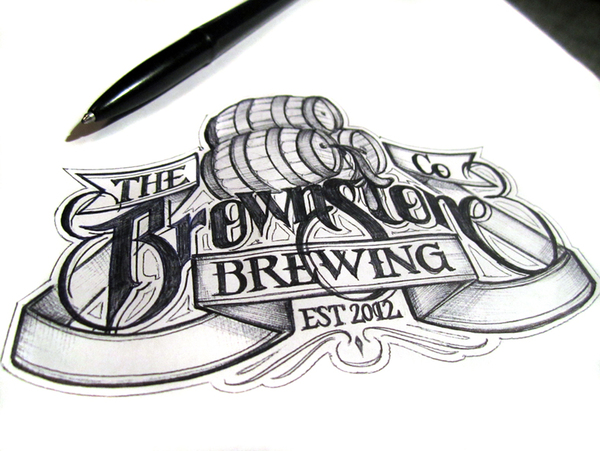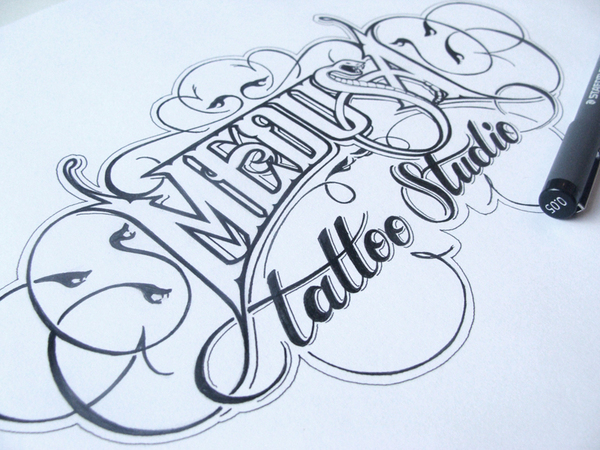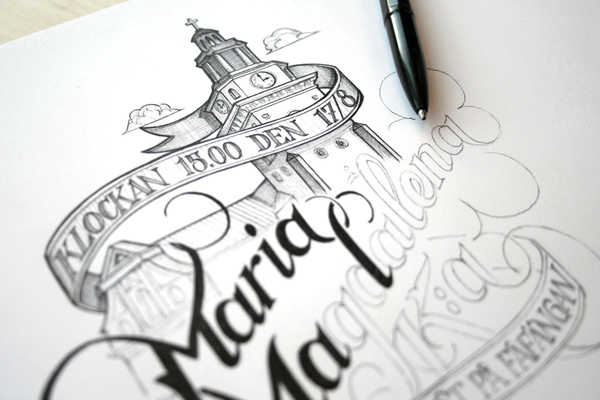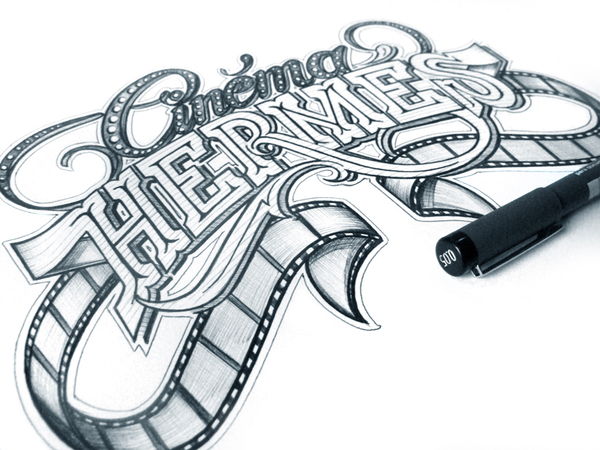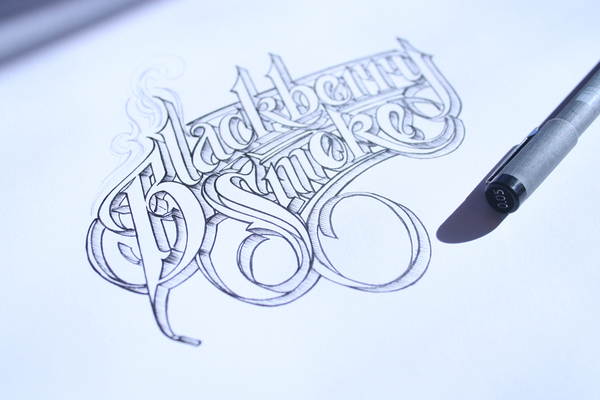
Martin Schmetzer
Por Lettering Time hemos visto pasar grandes diseñadores y artistas que realizan increíbles lettering a lápiz o a rotulador como Eric WaetzigAdam Romuald KłodeckiMaxwell Lord, pero a pesar de eso, no hemos podido remediar sorprendernos cuando hemos encontrado los trabajos de Martin Schmetzer  ya que son impresionantes, aquí os dejamos algunos de sus lettering: